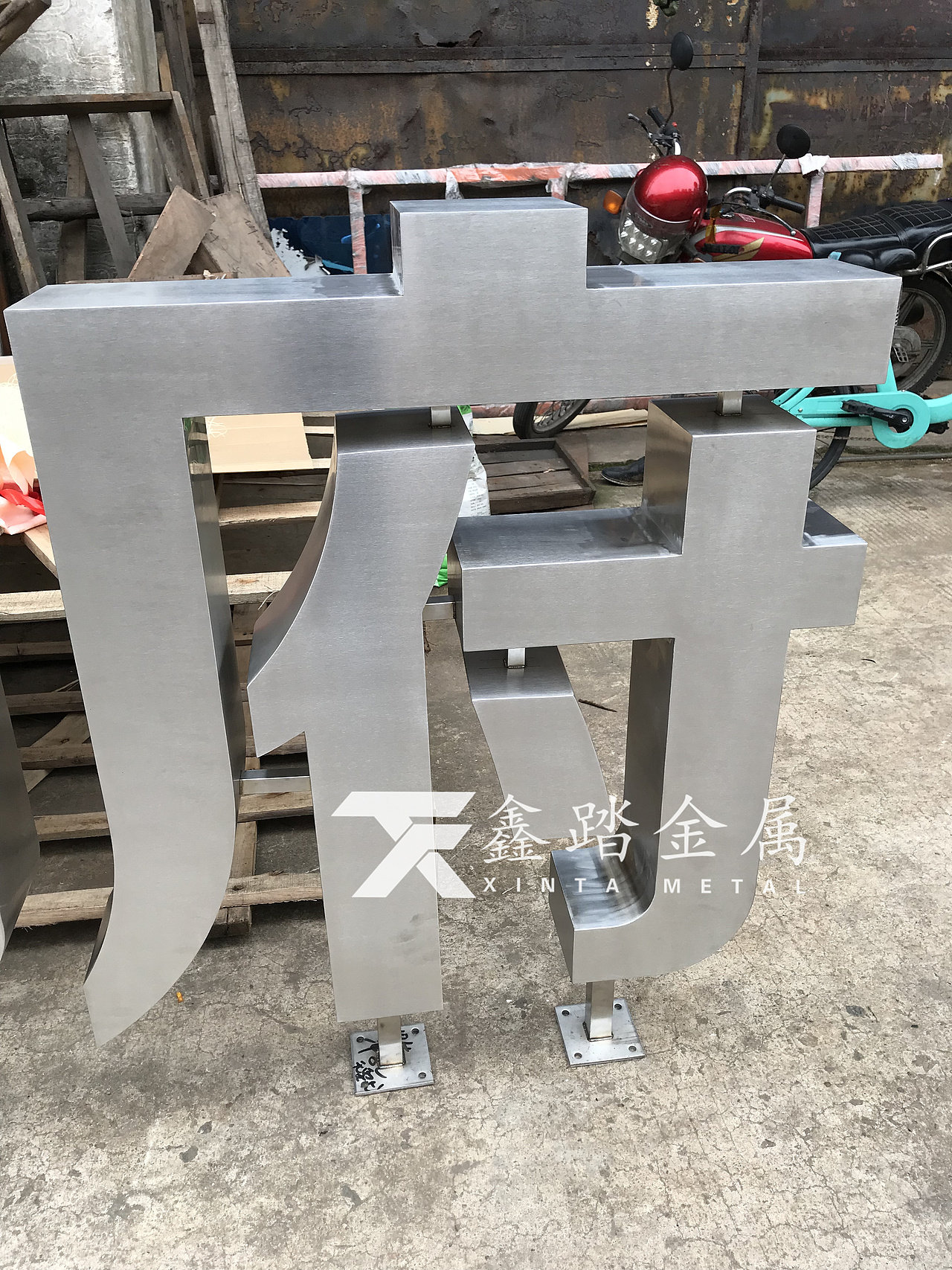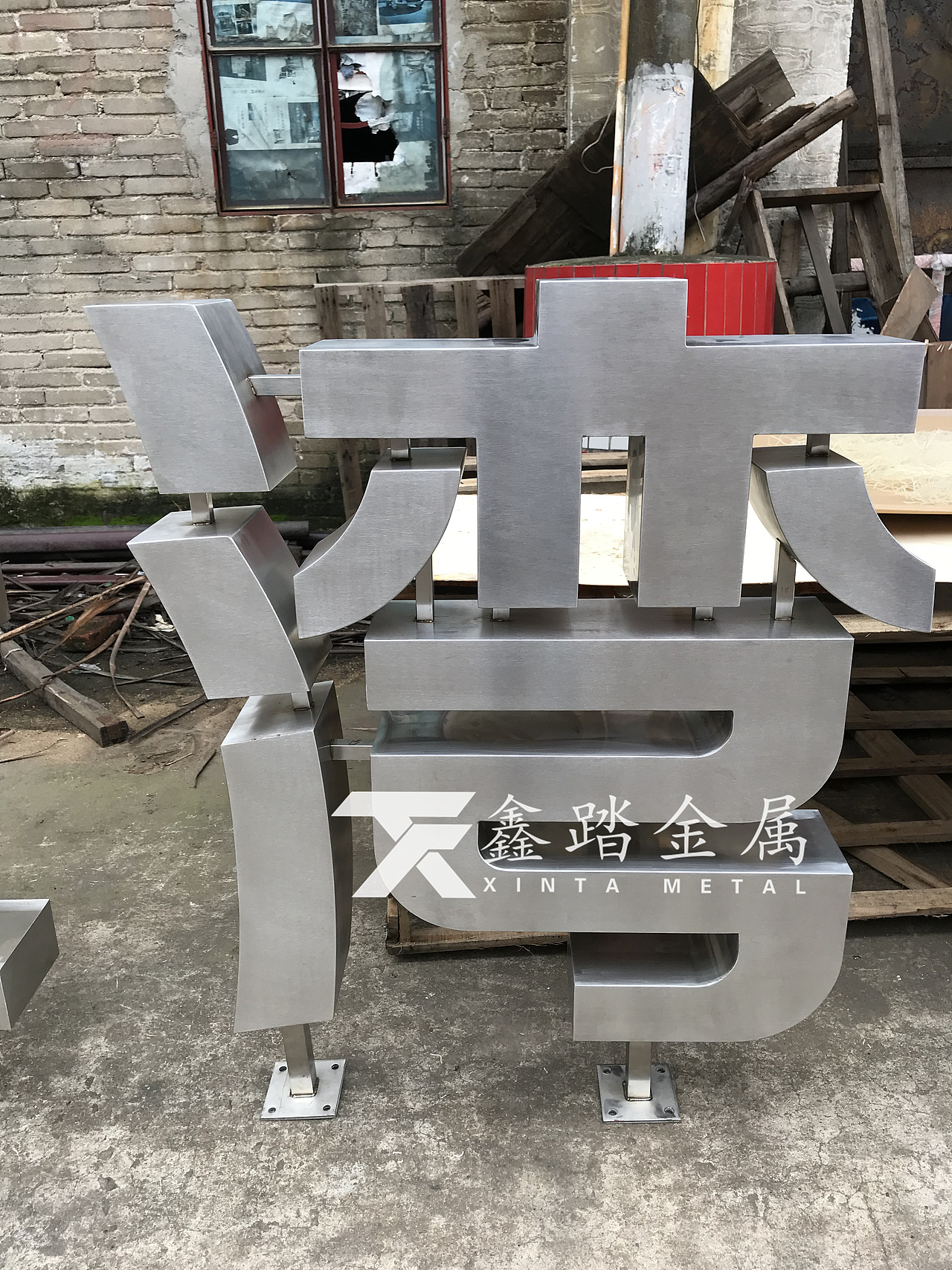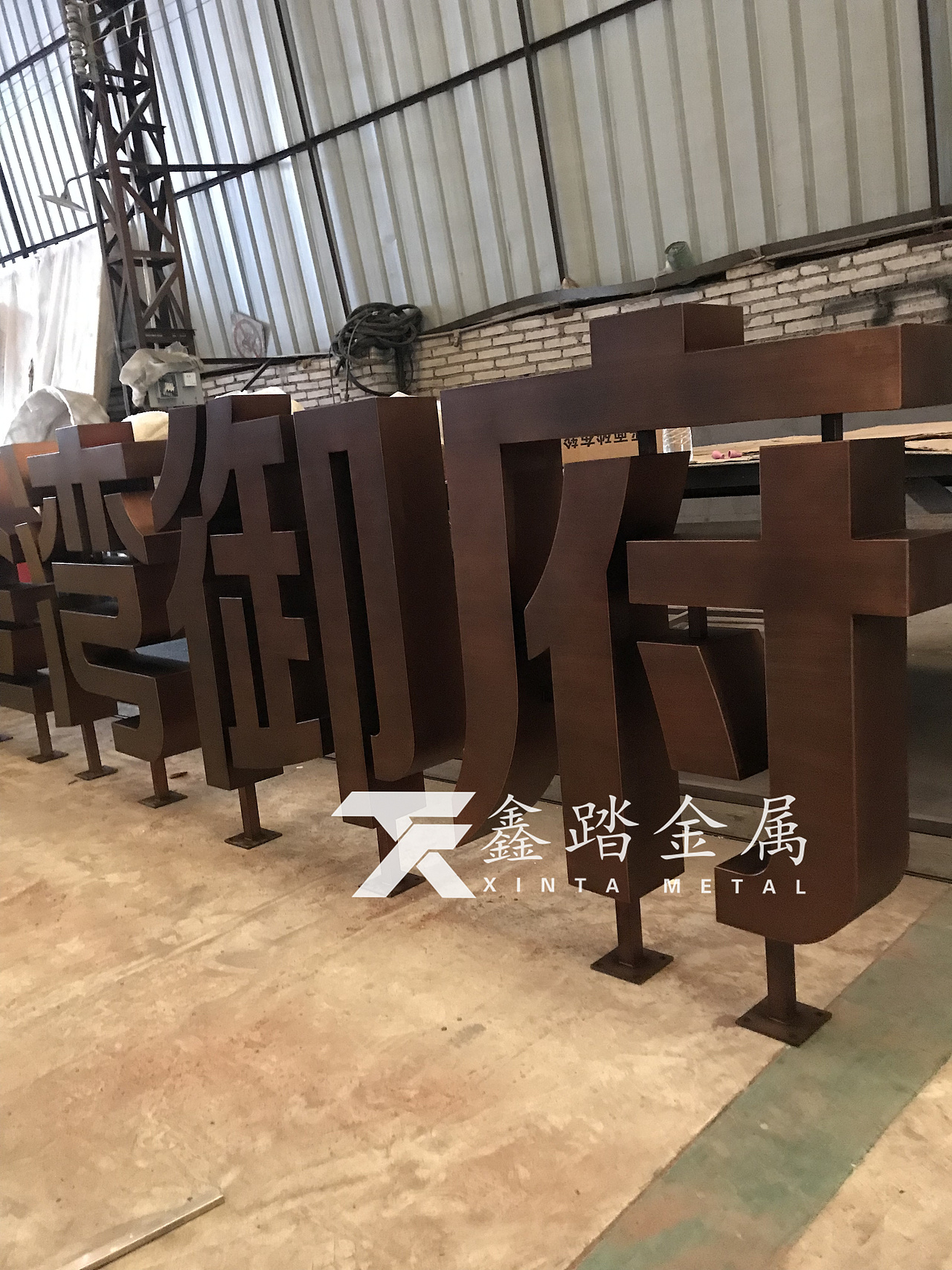
内外场合随处可见的不锈钢精工字体金属质感极强
拉丝不锈钢精工字是商场招牌、形象墙、标识标志、楼宇提示标识、各种高档品牌标识制作的首选产品之一,广泛的应用于户内外各场合。拉丝不锈钢精工字金属质感、立体感极强,大方、气派,具极佳的视觉效果;做工精细,每一道工序对技艺的要求都很高;特别适合于高档品牌形象展示,尽显豪华、尊贵,彰显品位与实力。